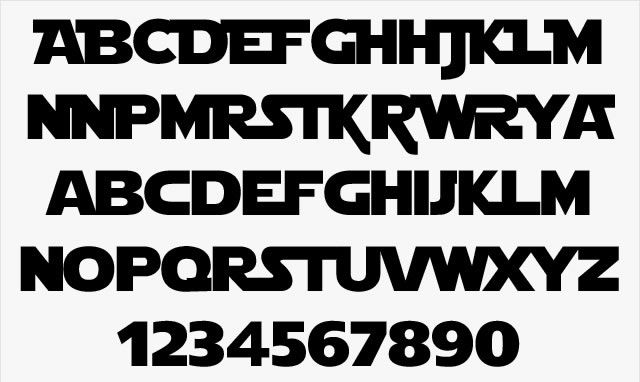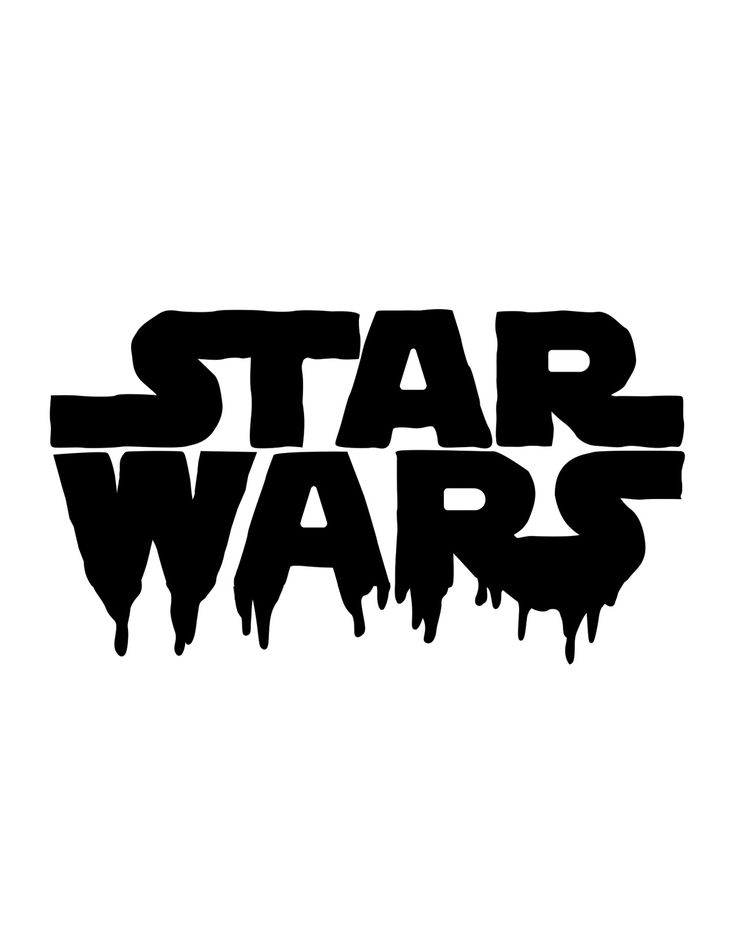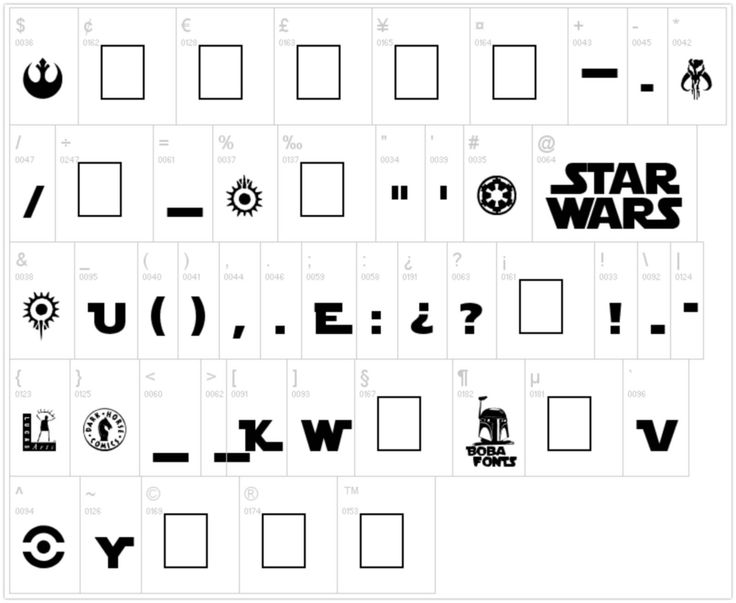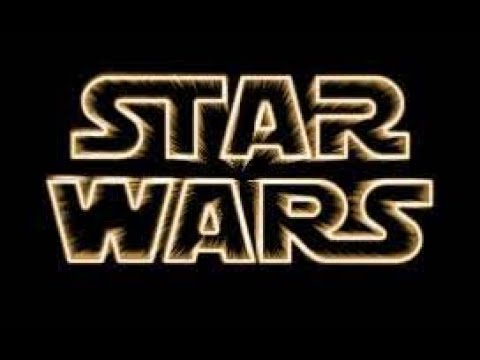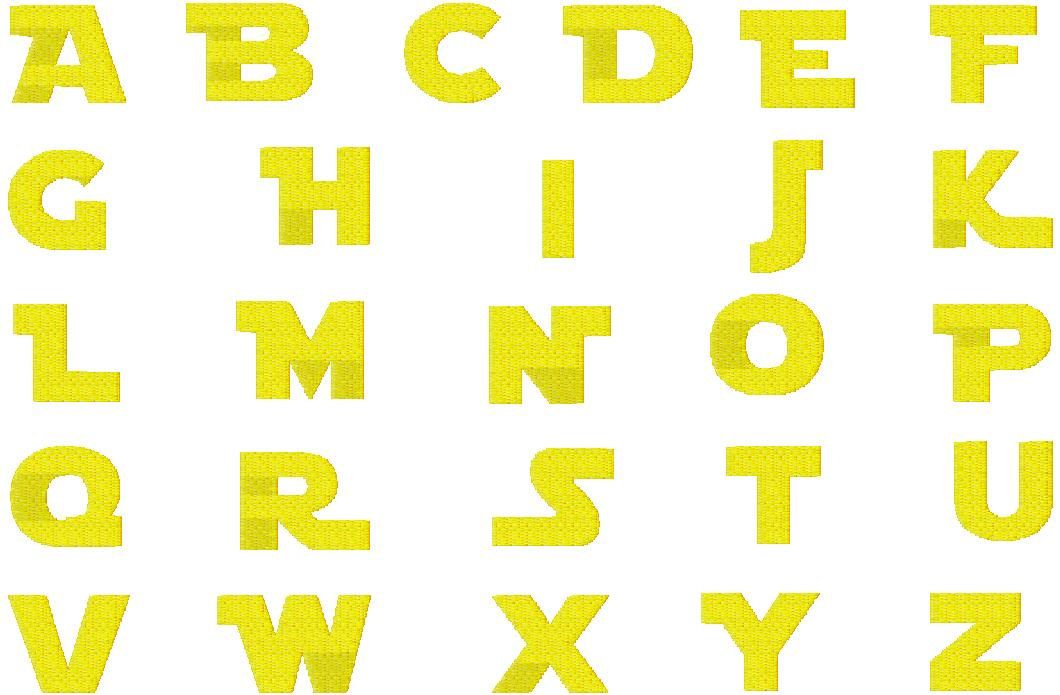
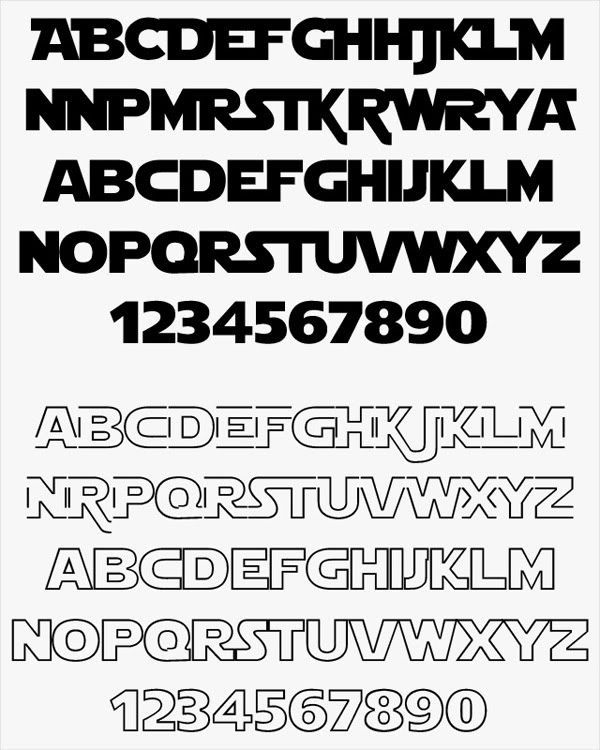
Логотип «Звездных войн» показывает, насколько сериал популярен во всем мире.
Символы зависят от интерпретации. Эмблема служит напоминанием о том, что какими бы значительными ни казались события, они всего лишь краткая остановка на бесконечном пути вселенной. Чтобы узнать больше о логотипе «Звездных войн», вот информация об империи, восстании, республике и шрифте сопротивления, связанном с логотипом «Звездных войн».
Логотип Звездных войн
Фильмы, мультсериалы, видеоигры, комиксы и другие продукты космической оперы, связанные с джедаями, составляют известную медиа-франшизу «Звездных войн». Девять основных эпизодов и два дополнительных эпизода рассматривались как предки вселенной «Звездных войн». Был также выпуск в 1997 году для первого из них. Но перед этим компания 20th Century Fox выпустила книгу по сценарию, потому что не была уверена, насколько хорошо получится экранизация. Таким образом, желая заранее знать, получат ли они новинку. Давайте прочитаем, чтобы увидеть происхождение и историю логотипа «Звездных войн».
Оригинальный логотип «Звездных войн» 1977 года.
Логотип «Звездных войн» существует с 1970-х годов. Он стал представлять собой нечто большее, чем просто логотип компании; он также стал представлять понимание поп-культуры. Хотя смотреть на логотип сложно, людям, для которых он был создан, он всегда очень нравился.
Когда логотип «Звездных войн» впервые появился в 1976 году, мало кто смог его увидеть. Этот конкретный логотип был разработан Ральфом МакКуорри и имеет белый фон с черным логотипом. Это связано с тем, что он не был широко использован на киноафишах и продуктах, и большинство людей не знакомы с этим стилем. Несмотря на то, что дизайн был передовым, бизнес посчитал, что он слишком деликатный для сюжета франшизы. Заглавные буквы во втором логотипе «Звездных войн» намного крупнее и выглядят лучше, чем в первом.
Множество вариантов логотипа «Звездных войн» можно было использовать на плакатах и других рекламных материалах. Но самым узнаваемым вариантом был словесный знак, который был либо черным, либо желтым и, казалось, исчезал.
Оформление очень похоже на сценарий, который кинозрители обычно читают после первого акта. Даже на большинстве итераций постера фильма «Новая надежда» были изображены знаменитости (в виде белых точек). Это подчеркивало тему фильма, хотя многие маркетинговые активы по-прежнему отображались простым черным или желтым цветом.
Оригинальный логотип «Звездных войн», каким его в настоящее время узнают большинство людей, выделяется на любом носителе благодаря особо жирному шрифту. Благодаря умному и преднамеренному сочетанию слов компания смогла напомнить зрителям о сенсации, которую они испытали в начале фильма «Звездные войны».
Заключение